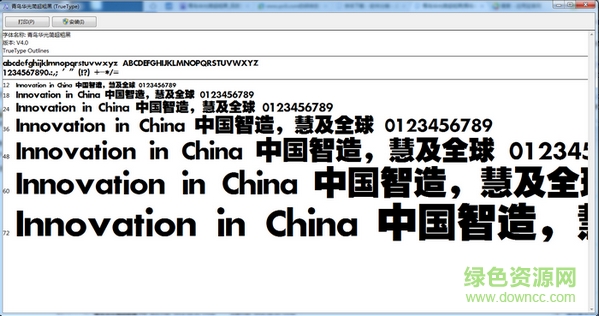
软件介绍 软件标签: 青鸟华光 字体 青鸟华光简超粗黑是一款常用的中文简体汉字,该字体的特色就是字形端正,线条粗壮有力,主要适用于广告设计、报纸杂志等,有需用的用户快来下载使用吧。安装方法:方法一:控制面板/字体/文件/安装新字体;方法二:直接将字体复制到C:\WINDOWS\Fonts。方法三:针对win7系统,用户只需选中字体右键安装即可。 软件截图 上一张下一张(1 / 1) 安装详细截图 猜你喜欢 粗黑字体 青鸟华光 粗黑字体 粗黑字体大全是小编为大家精心整理的字体合集,包含了市场上最美观最实用的几十款粗黑字体,这类字体没有衬线装饰,笔画清晰明朗,常常用于各行各业的文字排版设计方面! 查看更多>> 永中粗黑-普通 6.34M/中文/5.0/下载 小扣锐线粗黑字体 1.26M/中文/1.6/下载 粗黑体chinese gb2312 2.44M/中文/2.0/下载 lexus 简粗黑 u xbold 1.31M/中文/5.0/下载 碳纤维正粗黑简体字体 1.66M/中文/10.0/下载 义启粗黑体字体 10.00M/中文/10.0/下载 青鸟华光 青鸟华光是一款造型简约大方、严谨不失风趣的字体,本站为大家提供青鸟华光简超粗黑、青鸟华光简粗圆、青鸟华光简琥珀、青鸟华光简胖头鱼等免费下载,欢迎大家使用! 查看更多>> jpty 2.44M/中文/5.0/下载 青鸟华光繁方珊瑚 1.46M/中文/10.0/下载 青鸟华光简细圆字体 1.70M/中文/10.0/下载 青鸟华光淡古印繁体 4.04M/中文/10.0/下载 青鸟华光简魏体字体 2.92M/中文/10.0/下载 青鸟华光简姚体字体 1.38M/中文/10.0/下载 其他版本下载 标题 大小 更新日期 下载 下载地址 电脑版 青鸟华光简超粗黑 免费版 点击报错 软件无法下载或下载后无法使用,请点击报错,谢谢! 关闭报错反馈 请描述您所遇到的错误,我们将尽快予以修正,谢谢! *必填项,请输入内容 本类最新 dreamweaver字体库 首尔南山体字体 v1.06 官方版 潮字社风云简ttf 潮字社凌渡鲲鹏简体字体 潮字社曾玉波手书简字体 微博慧心字体 相关文章 Photoshop字体安装使用方法和技巧 如何解决“无法新增字体”问题 Win 7系统安装字体方法 网页字体大小设置方法 怎么改网页字体大小 在Linux系统中安装字体的几种方法 windows7字体显示问题:打开某些程序的时候显示的是乱码 用户评论 热门评论 最新评论 发表评论 查看所有评论(0) 昵称: 请不要评论无意义或脏话,我们所有评论会有人工审核. 字数: 0/500 (您的评论需要经过审核才能显示)